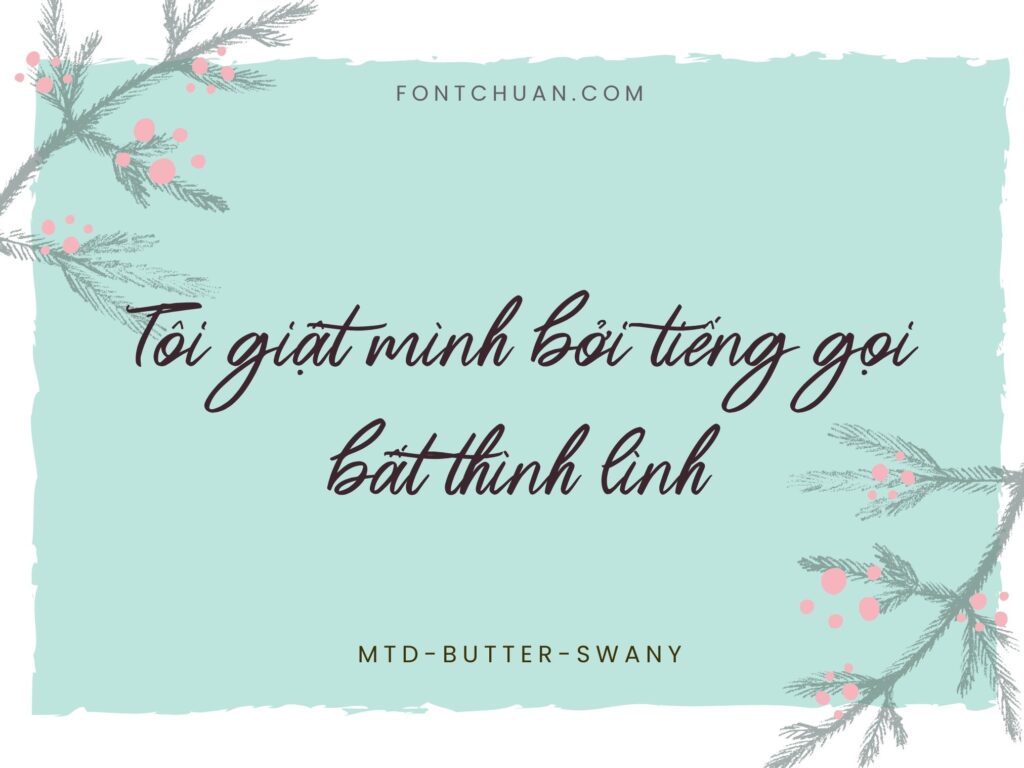
Font MTD Butter Swany Việt Hóa
Font MTD Butter Swany là một kiểu chữ viết tay mang phong cách brush, được thiết kế bởi FHFont và đã được Việt hóa bởi Mộc Hạ. Font này hỗ trợ đầy đủ tiếng Việt cùng hơn 90 ngôn ngữ khác, mở rộng khả năng ứng dụng trong các thiết kế đa ngôn ngữ. Đây là một trong những phông chữ được cộng đồng thiết kế đánh giá cao và sử dụng trong nhiều dự án sáng tạo, đáp ứng nhu cầu đa dạng của người dùng.
MTD Butter Swany nổi bật với các đường nét mềm mại và tự nhiên, tạo cảm giác thân thiện và gần gũi. Font rất phù hợp cho các thiết kế logo, tiêu đề, bao bì sản phẩm, thiệp mời và các ấn phẩm đòi hỏi sự tinh tế và nghệ thuật. Các ngành nghề phù hợp bao gồm quảng cáo, giáo dục, công nghệ, thiệp cưới và ảnh cưới. Font này cũng lý tưởng cho các sự kiện như Tết, Giáng sinh, Valentine và các lễ hội khác.